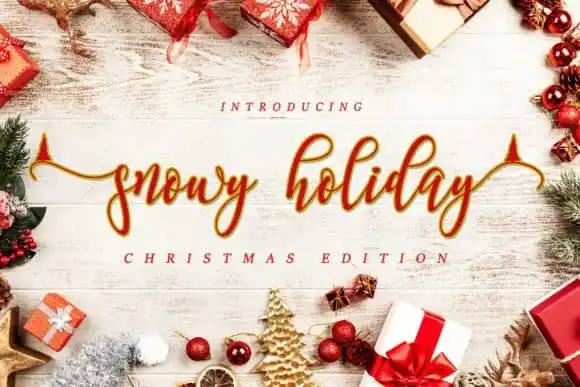
Snowy Holiday Calligraphy Font – Download Grátis
A Snowy Holiday Calligraphy Font é uma fonte delicada e elegante com traços fluidos e bem equilibrados. Ela combina perfeitamente com vários estilos, especialmente aqueles que valorizam um clima natalino agradável. Esta tipografia foi criada por tinyhandletter, disponível através do site 99designs. O que destaca esta fonte são suas linhas suaves e os detalhes exuberantes nos caracteres, especialmente nas formas finais dos traços. Ela apresenta um acabamento de letra discreto que se torna ainda mais notável ao longo da linha. Este tipo de fonte é perfeita para letras individuais ou cartões de agradecimento natalinos. A Snowy Holiday Calligraphy Font, como o nome sugere, inclui uma tonalidade especial no início e fim dos traços que torna a escrita ainda mais convidativa e apropriada para o clima festivo. Ela é perfeita para aqueles desejando um touch delicado e elegante em suas mensagens natalinas ou até mesmo para aqueles que querem uma fonte de escrita de mão bem feita para cartões de agradecimento.